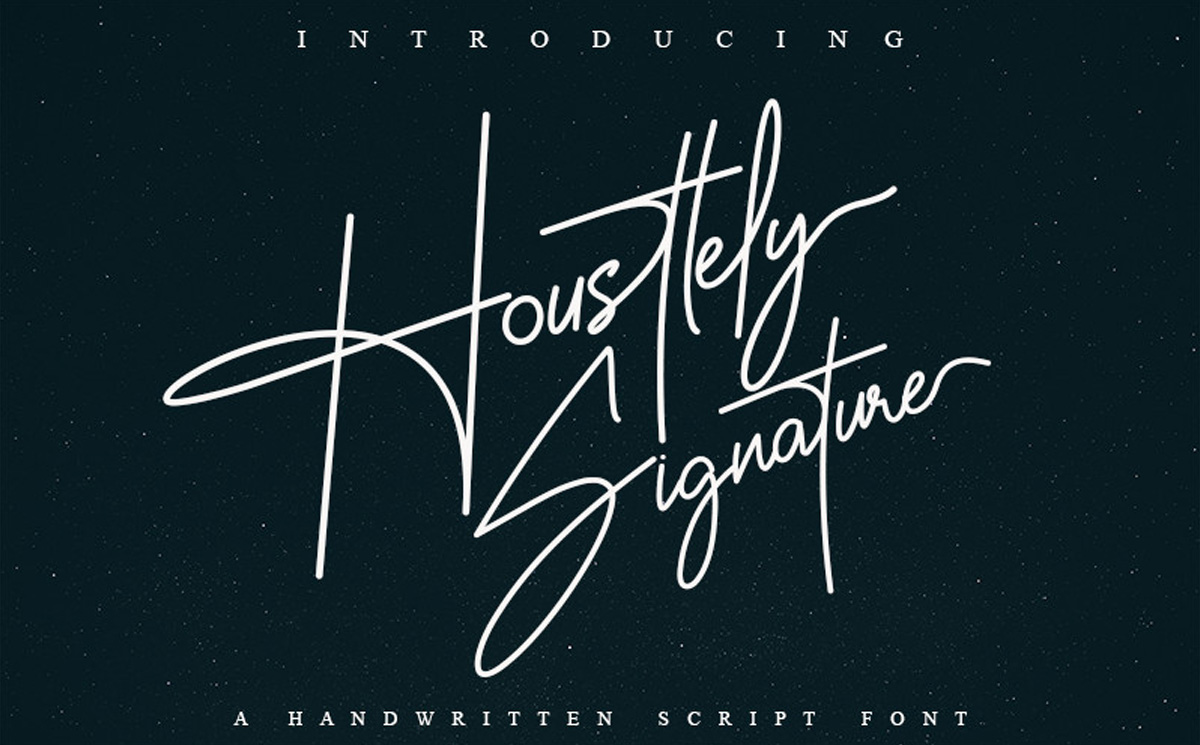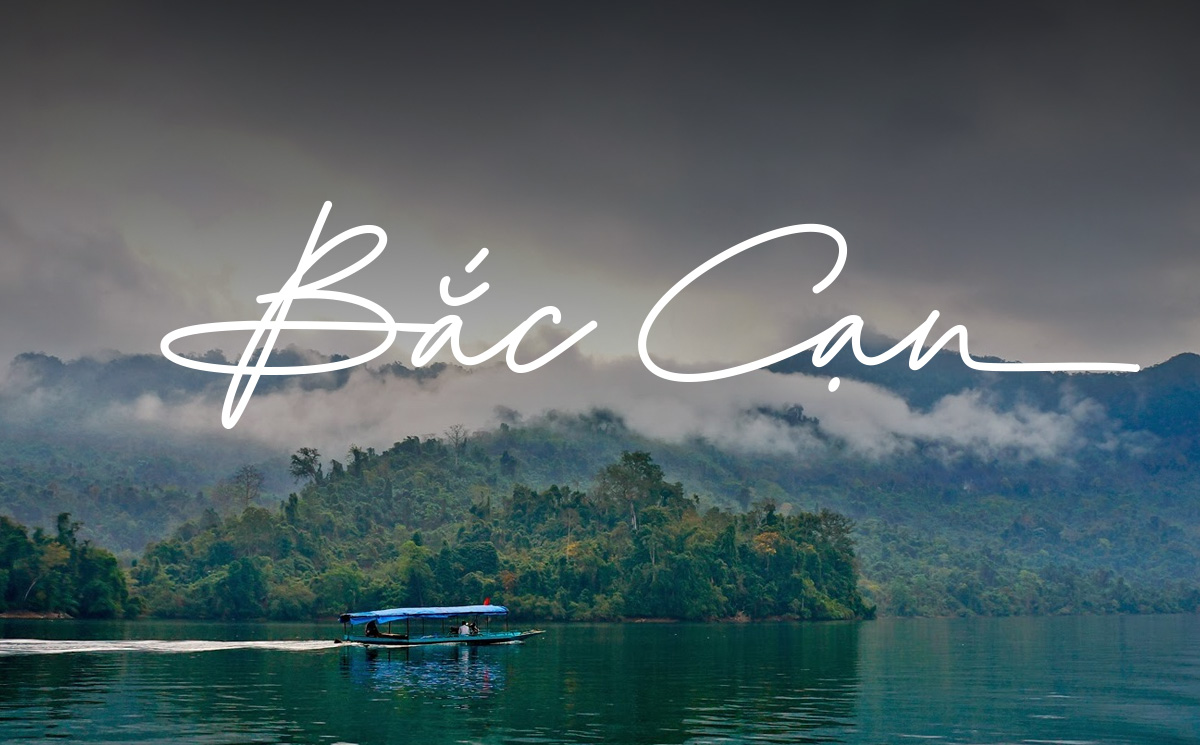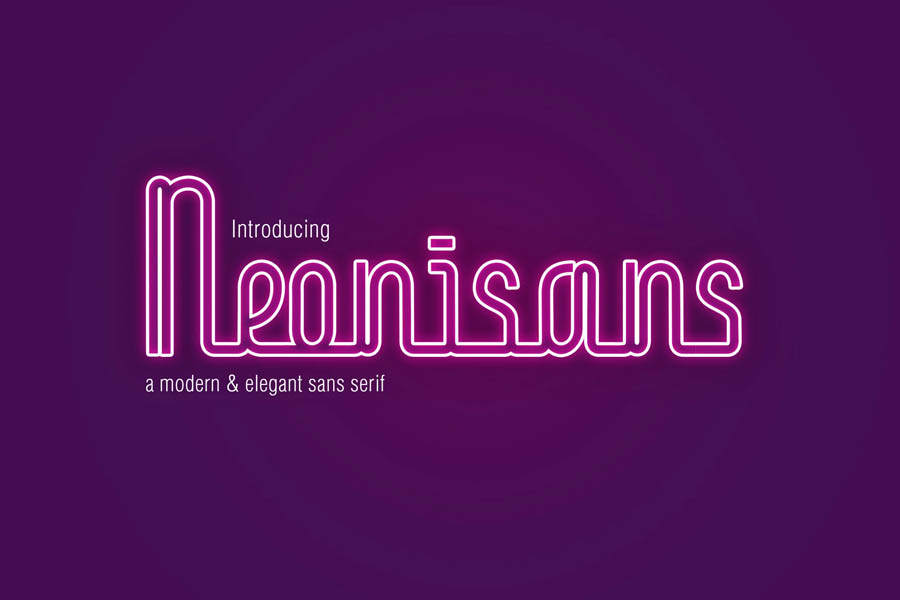
17+ Font Chữ LED Neon Phát Sáng Việt Hóa Đẹp Nhất 2025
Khám phá top font LED Neon Việt hóa & quốc tế đẹp 2025, mô phỏng đèn neon ấn tượng, dễ dùng cho thiết kế cá nhân & chuyên nghiệp.
Khi nhắc đến những kiểu chữ LED Neon với hiệu ứng phát sáng độc đáo, đường nét uốn cong bắt mắt và tinh thần đậm chất nightlife, những bộ font này không chỉ làm nổi bật tiêu đề, mà còn mang lại cảm giác hiện đại, có chút hoài cổ và đầy sáng tạo.
Trong bài viết này, Fontdep.vn sẽ giới thiệu đến bạn top các font LED Neon Việt hóa và chưa Việt hóa đẹp nhất 2025, dễ dùng, dễ tải và phù hợp cho cả thiết kế cá nhân lẫn chuyên nghiệp. Dù bạn đang cần font cho poster sự kiện, bảng hiệu quán bar hay một bìa podcast mang đậm cá tính, danh sách này chắc chắn sẽ mang đến nguồn cảm hứng rực rỡ.
Font LED Neon là gì?
Font LED Neon là kiểu chữ được thiết kế để mô phỏng hiệu ứng phát sáng của đèn neon – loại đèn thường thấy trong các bảng hiệu quán bar, poster sự kiện, hay không gian mang phong cách nightlife và retro. Điểm nổi bật của dòng font này nằm ở đường nét bo tròn mềm mại, hiệu ứng glow phát sáng ảo và màu sắc rực rỡ như hồng, tím, xanh dương hoặc vàng điện tử.
Bước sang năm 2025, font chữ LED Neon không chỉ được ưa chuộng trong các thiết kế liên quan đến âm nhạc, nightlife hay công nghệ, mà còn trở thành xu hướng thiết kế đồ họa cá tính, nơi cảm xúc và ánh sáng hòa quyện. Từ thiệp mời sinh nhật, poster EDM, cho đến logo quán cà phê mang hơi hướng hiện đại – kiểu chữ này luôn mang lại cảm giác nổi bật, năng động và đầy nghệ thuật.
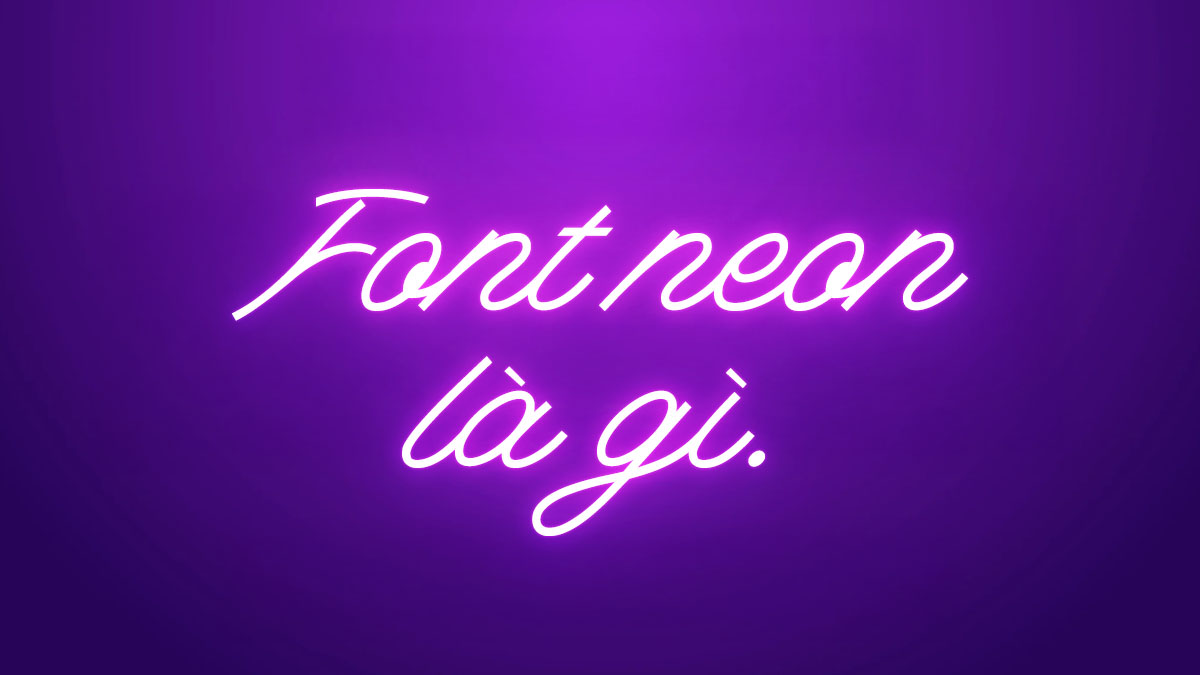
Những đặc trưng nổi bật của font chữ LED Neon
Khi nhắc đến font LED Neon, người ta nghĩ ngay đến những kiểu chữ bắt mắt, phát sáng và đầy cá tính. Dưới đây là những đặc điểm nhận diện dễ thấy nhất của dòng font này:
- Đường nét mảnh, bo cong đều: Font LED Neon thường được thiết kế với đường nét thanh mảnh, mô phỏng hình dạng ống đèn uốn cong – tạo cảm giác mềm mại nhưng vẫn nổi bật.
- Hiệu ứng glow phát sáng: Đặc trưng nổi bật nhất là hiệu ứng ánh sáng ảo quanh chữ. Lớp phát sáng này giúp chữ trông như đang tỏa sáng trên nền tối, mang lại chiều sâu và sự thu hút thị giác.
- Màu sắc rực rỡ, nổi bật: Các font LED Neon thường sử dụng những gam màu như hồng neon, tím neon, xanh dương điện tử hoặc vàng chanh – rất phù hợp với thiết kế cần gây ấn tượng mạnh.
- Phong cách đậm chất nightlife và retro điện tử: Từ cảm hứng bảng hiệu quán bar, tiệm karaoke đến phong cách thập niên 80s – font LED Neon thường gắn liền với sự sôi động, sáng tạo và không khí thành thị về đêm.
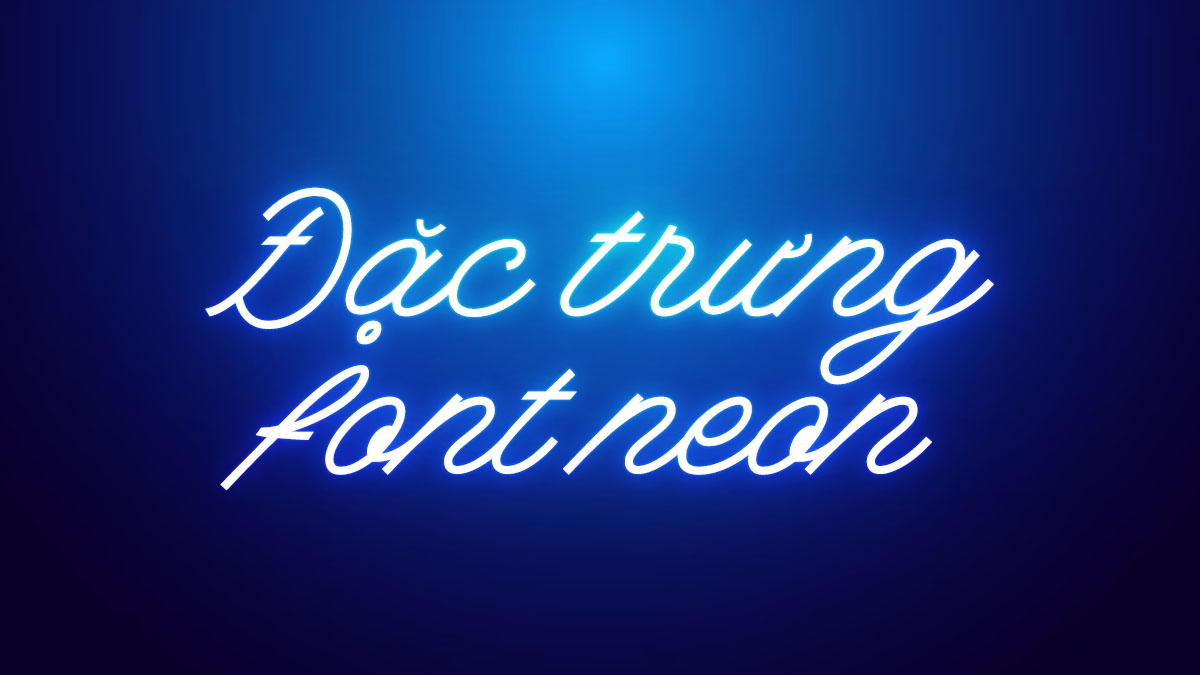
Danh sách font LED Neon Việt hóa
Dưới đây là những font chữ LED Neon đã được Việt hóa hoàn chỉnh, có thể sử dụng ngay cho nội dung tiếng Việt. Mỗi font đều mang phong cách riêng, phù hợp với nhiều loại thiết kế từ cá nhân đến chuyên nghiệp.
1. Font Motherland Signature – Viết tay thanh mảnh, giàu cảm xúc
Với nét chữ mềm mại và nghiêng nhẹ, Motherland Signature mang đến cảm giác như được viết bằng bút lông đầu nhỏ. Các đường nét mảnh nhưng rõ ràng, đặc biệt là nhịp điệu thị giác uyển chuyển. Font này rất lý tưởng cho tiêu đề poster nhạc, trích dẫn cảm xúc hoặc thiết kế in ấn có chiều sâu nghệ thuật.
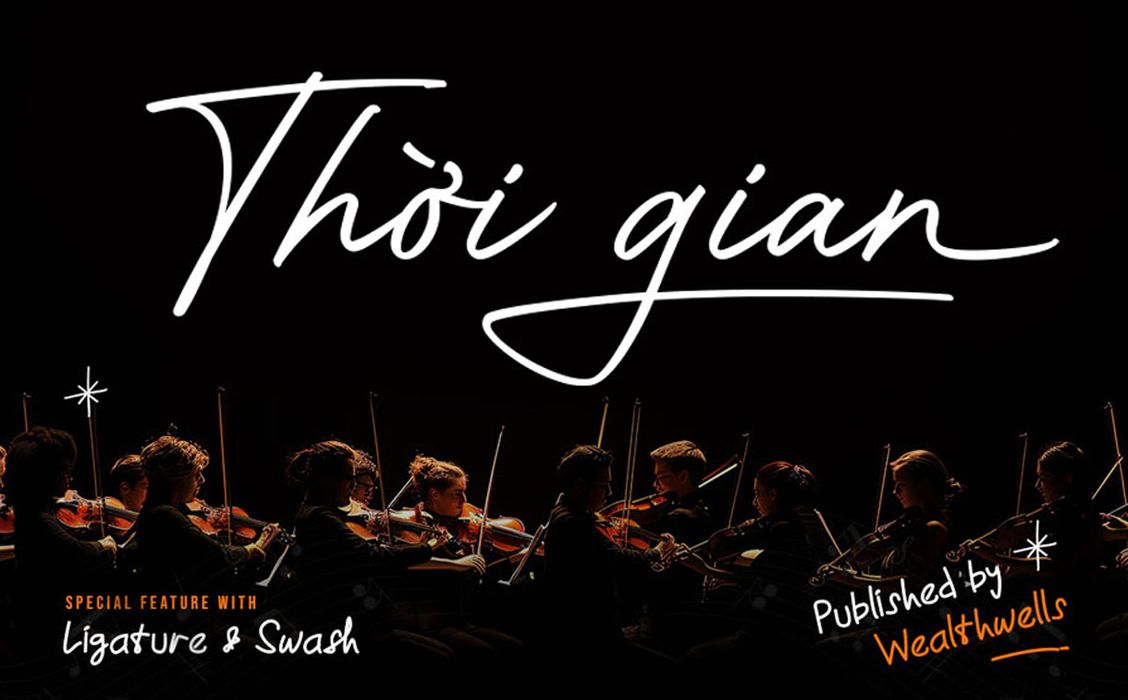
2. VL Selfie – Retro thanh lịch, đậm chất châu Âu
VL Selfie mang phong cách cổ điển với nét bo tròn nhẹ và sự xuất hiện của swash cùng ligature. Các ký tự có độ tương phản vừa đủ, gợi nhớ đến typography trên các biển hiệu xưa. Font rất phù hợp để thiết kế thiệp cưới, tiêu đề lookbook, hoặc thương hiệu cần yếu tố thanh lịch.
- Tác giả: Maximiliano Sproviero
- Việt hóa bởi: Team VL
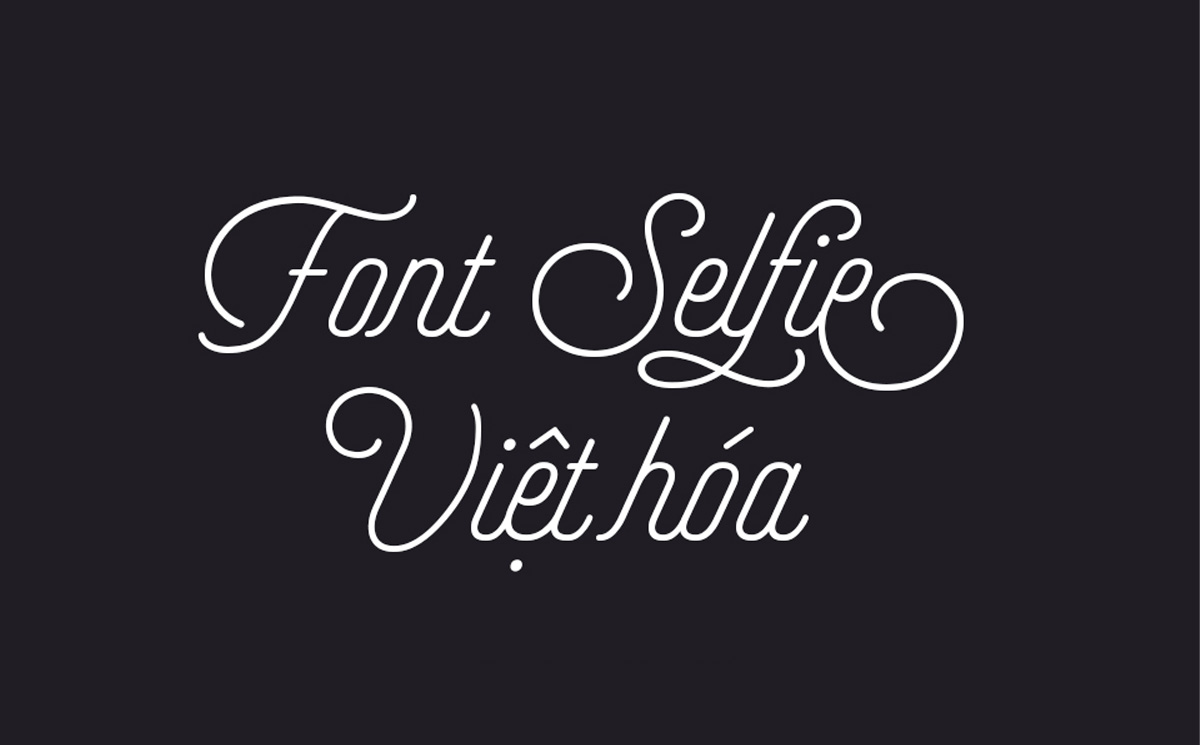
3. Histerm – Chữ ký hiện đại, tinh gọn
Histerm là font chữ ký cao cấp, có đường nét kéo dài mảnh mai và độ thưa hợp lý. Dù đơn giản, font vẫn tạo được điểm nhấn khi dùng trên nền tối hoặc trong thiết kế hồ sơ cá nhân, watermark và logo tối giản.
- Tác giả: Yudi Pratama Chandra
- Việt hóa bởi: Phạm Sơn
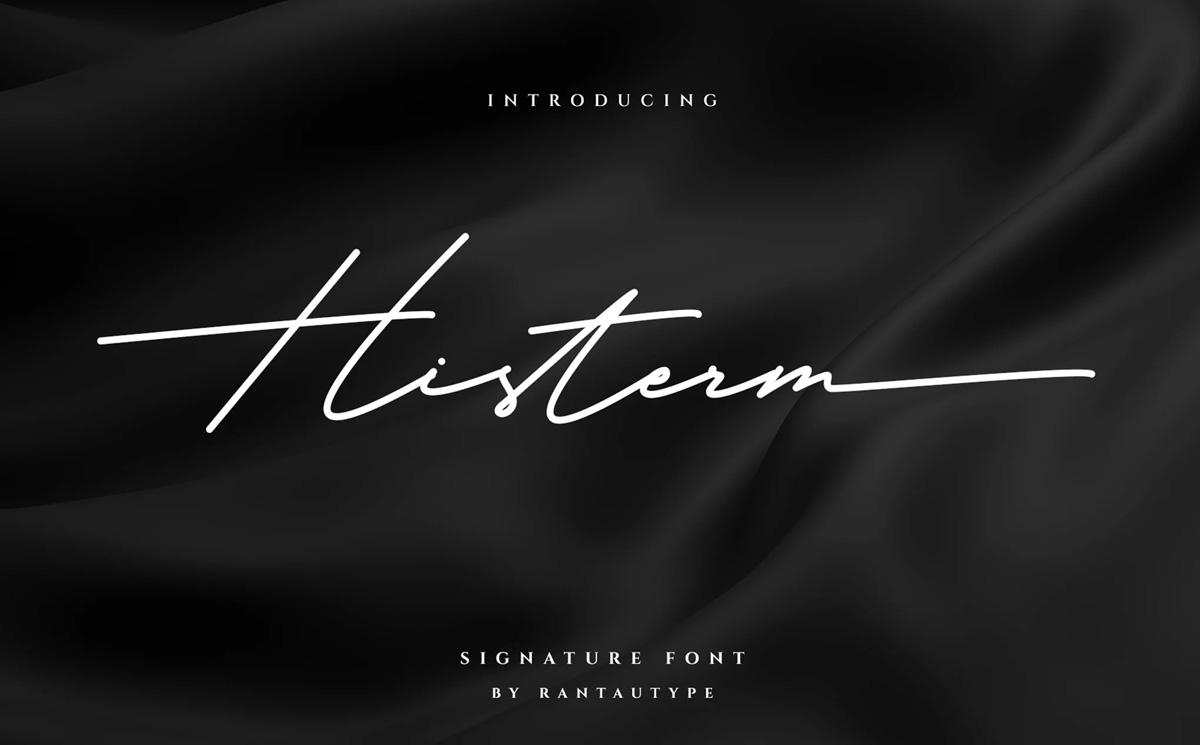
4. SVN Rankstone – Năng động, hiện đại, đậm chất lifestyle
Rankstone kết hợp giữa nét chữ cao và bo tròn, tạo nên phong cách trẻ trung và cân đối. Font nghiêng nhẹ, rõ ràng và dễ đọc, rất phù hợp với thiết kế thời trang, blog cá nhân, bìa sách hoặc thương hiệu mang hơi hướng cá nhân hóa.
- Việt hóa bởi: SVN Team
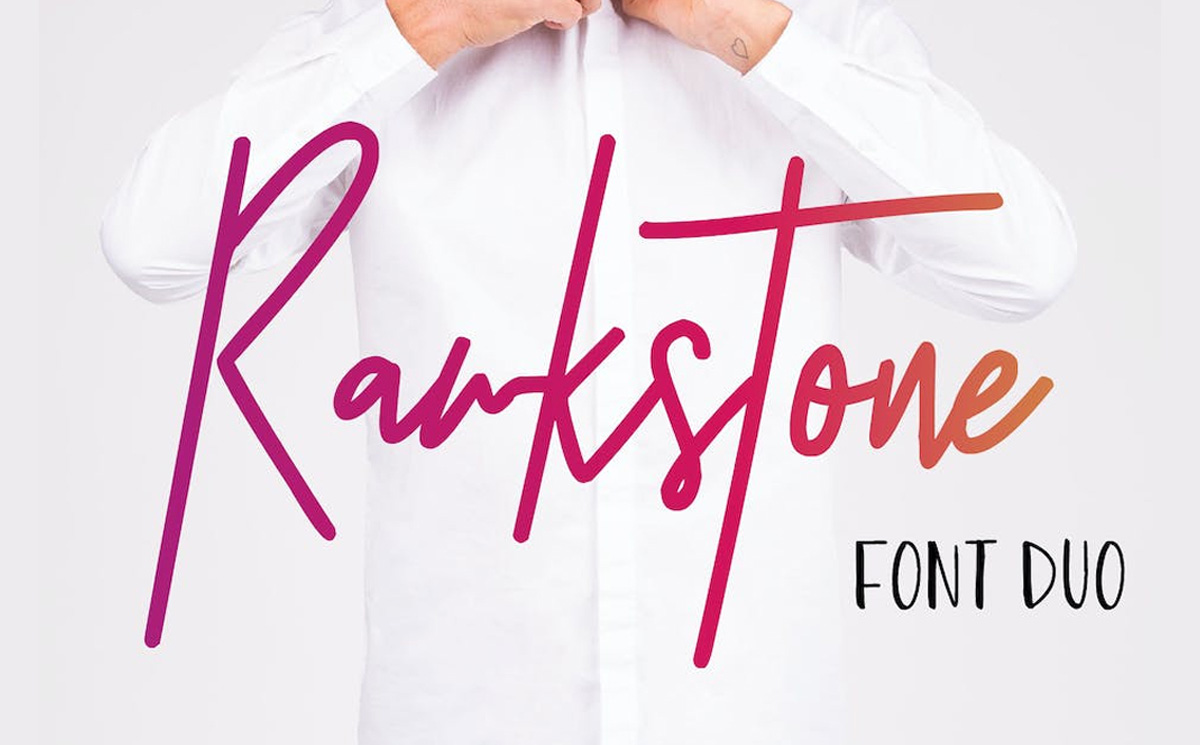
5. SVN Kelso – Neon hình học mạnh mẽ, cá tính thị giác
Kelso là font LED Neon mang phong cách hình học chắc chắn với các ký tự vuông vức, rõ ràng. Hiệu ứng phát sáng được xử lý tinh tế, giúp font trở nên nổi bật khi đặt trên nền tối hoặc hình nền tương phản mạnh. Rất lý tưởng cho tiêu đề poster công nghệ, banner EDM, hoặc bảng hiệu thương hiệu nightlife.
- Tác giả: Adrian Talbot
- Việt hóa bởi: SVN Team
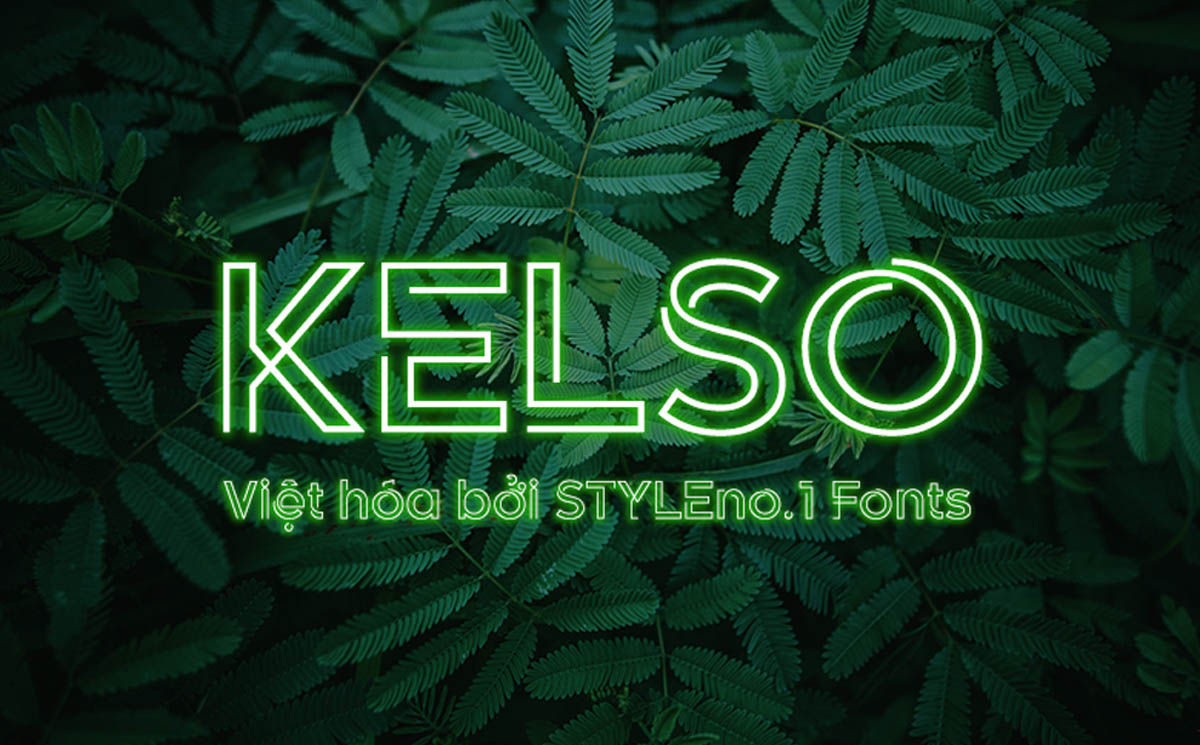
6. SVN Housttely Signature – Chữ ký táo bạo, khác biệt
Với nét chữ uốn cong mạnh mẽ và kéo dài táo bạo, Housttely Signature tạo nên sự phóng khoáng và cá tính. Font phù hợp với những thiết kế cần điểm nhấn cá nhân như ảnh bìa blog, tiêu đề lifestyle, hoặc chữ ký trên ấn phẩm nghệ thuật.
Thế giới font chữ luôn không ngừng thay đổi, nhưng font LED Neon vẫn luôn giữ được sức hút riêng nhờ khả năng kết nối cảm xúc bằng ánh sáng và kiểu dáng. Dù bạn theo đuổi phong cách thiết kế hoài cổ, công nghệ, hay đơn giản là muốn gây ấn tượng trong một tiêu đề duy nhất – những bộ font LED Neon Việt hóa mà Fontdep.vn chia sẻ hôm nay chính là công cụ lý tưởng để bạn thổi hồn vào từng chi tiết.
Đừng ngần ngại tải về và thử nghiệm từng font – bởi chỉ một chút ánh sáng từ kiểu chữ phù hợp, thiết kế của bạn cũng có thể... tỏa sáng rực rỡ.